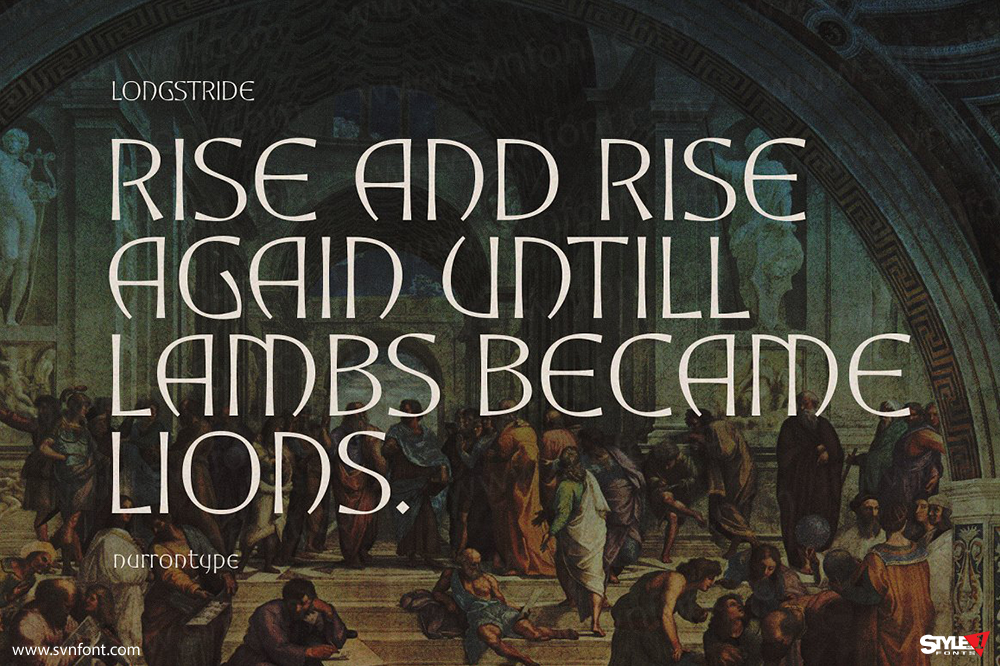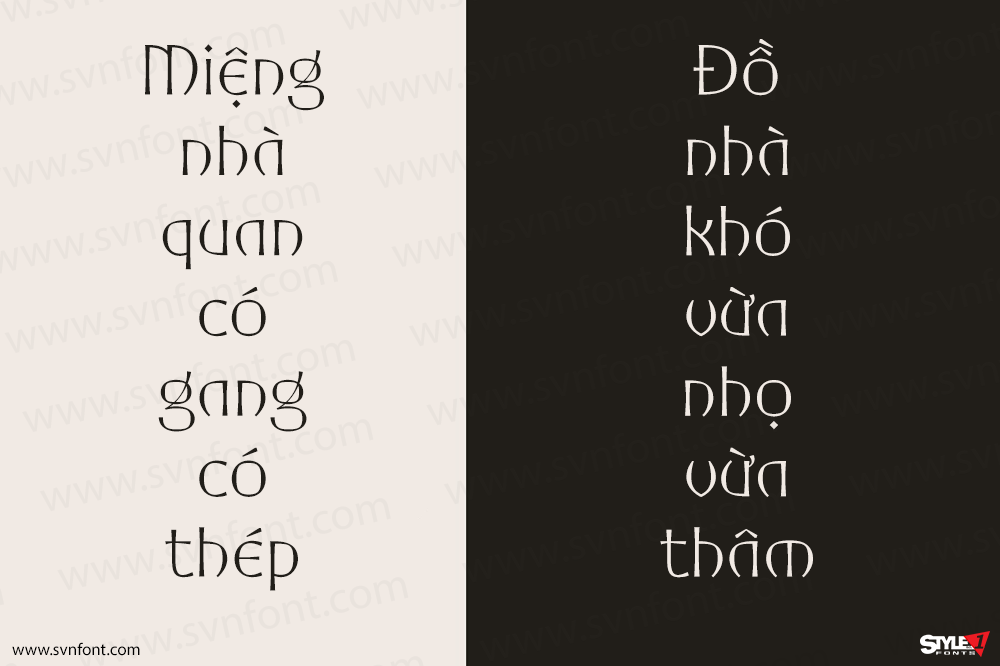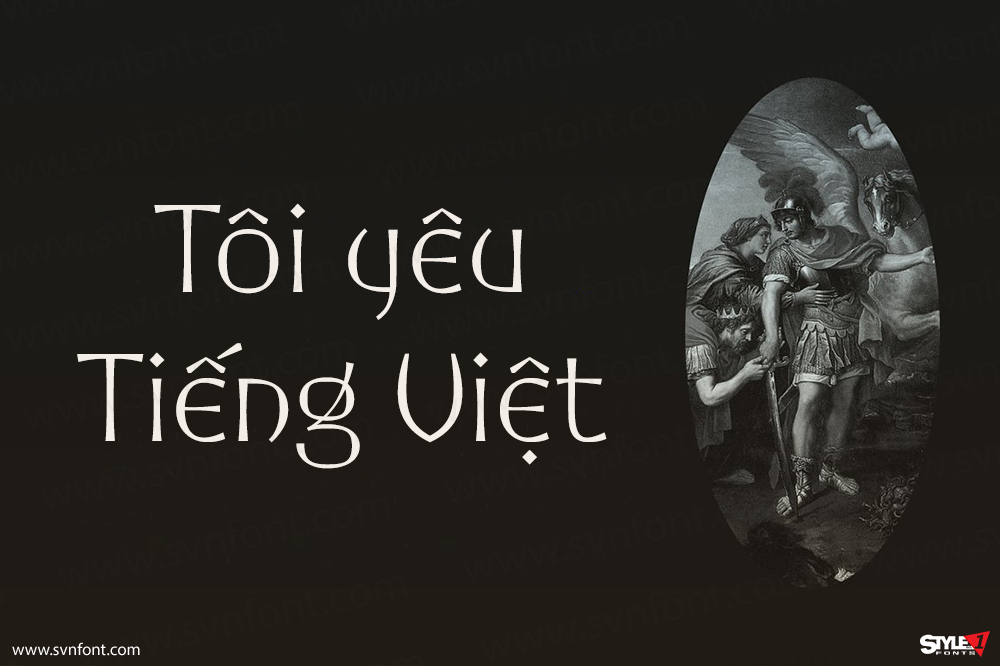
Longstride được lấy cảm hứng từ hình dáng chữ La Mã, là một typeface độ tương phản thấp, mang cá tính rõ rệt. Font hỗ trợ chữ hoa, chữ thường, small caps, chữ số và đa ngôn ngữ. Ngoài ra, Longstride còn được bổ sung ligature và các ký tự thay thế (alternates), giúp tăng tính linh hoạt và sáng tạo khi sử dụng trong các dự án thiết kế.
Nhà thiết kế: Nurron
Nhà phát hành: Nurrontype